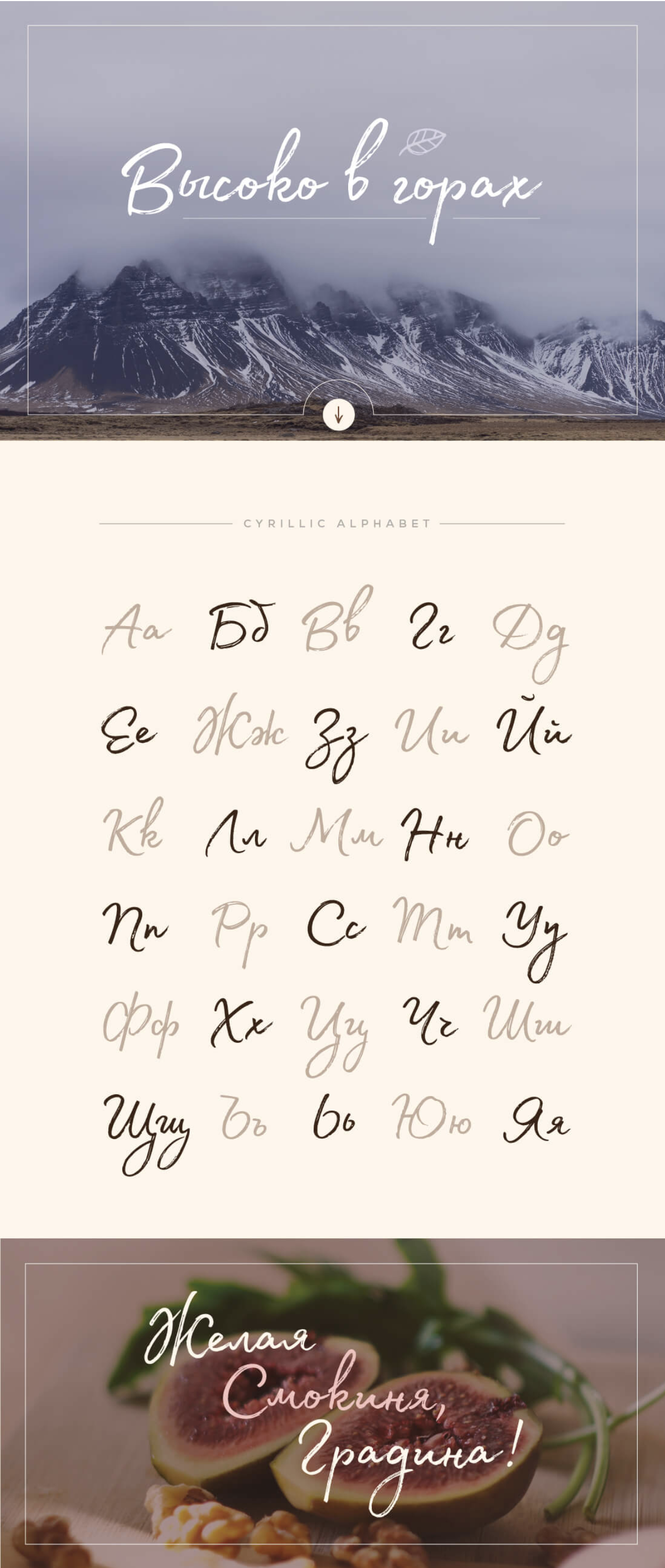
Красивый рукописный кириллический шрифт + 120 языков
Шрифт очень хорош, как и глифы. Материал на уровне! Хотя буква "к" все-таки подвела, но это мелочи. Оргу респект за проделанную, как всегда, отличную складчину.
Шрифт просто восхитительный! К нему также идёт множество интереснейших глифов! Безмерная благодарность за организацию складчины @Klaviaturos :-)
Только мне кажется, что строчная буква "к" в кириллице никогда не имела подобного написания?